ビジネスチャットツール「Slack」では絵文字でのリアクション機能などがあり、デフォルトの絵文字に加えてカスタム絵文字を登録することができます。
「お願いします」「ありがとうございます」などのカスタム絵文字はちょっとした受け答えにも使えて便利です。しかし、小さな正方形にテキストを収めるため過度な長体変形がされているケースを目にします。そこで今回は、字幅のバリエーションが用意されているタイププロジェクトのフォントで、長体変形をせずにカスタム絵文字を作ってみました。
ピックアップしたのは、元より長体で設計されたファミリーがあるAXISラウンド 100とTPスカイ ミドルコントラストの2シリーズです。
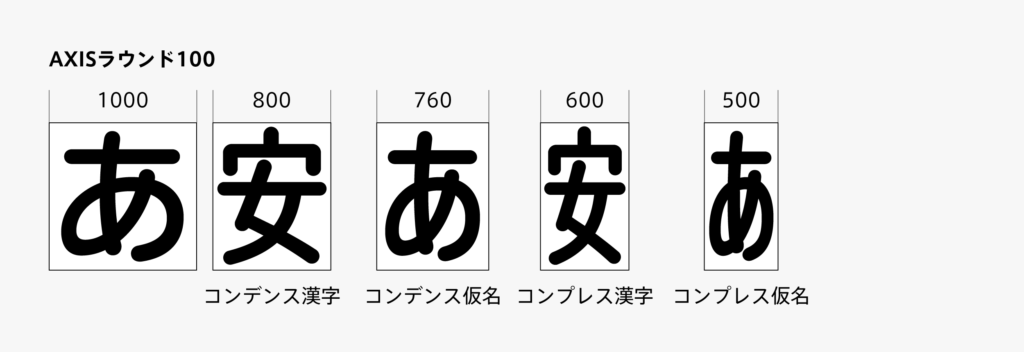
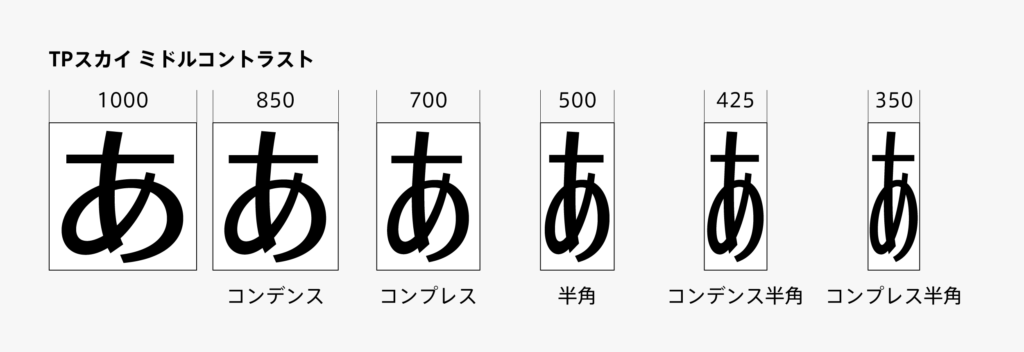
完成したカスタム絵文字がこちら(左側)、長体変形で作ったもの(右側)も並べてみました。AXISラウンド 100は丸みのあるSlackのUIに似合いそうです。TPスカイ ミドルコントラストはスッキリとした印象でビジネスシーンにも馴染みが良いかと思います。